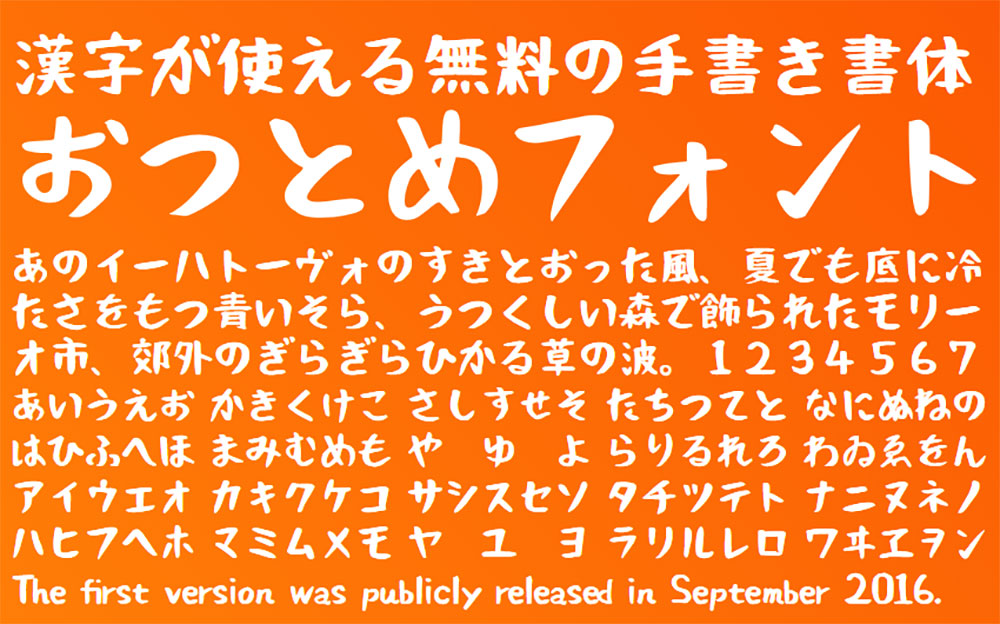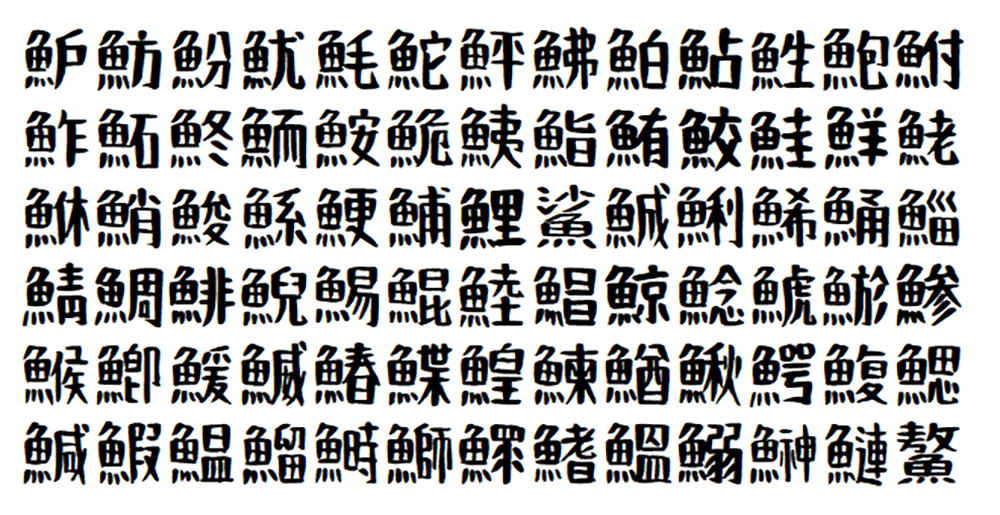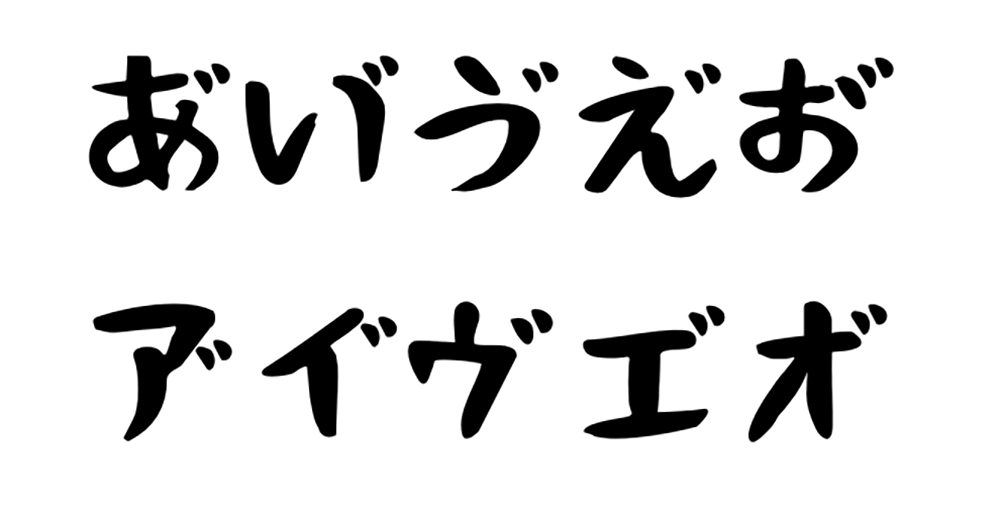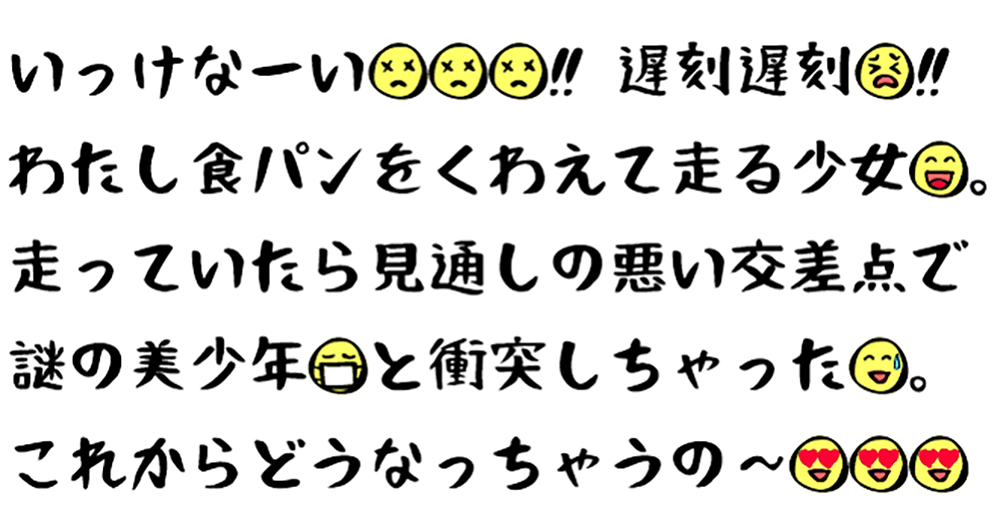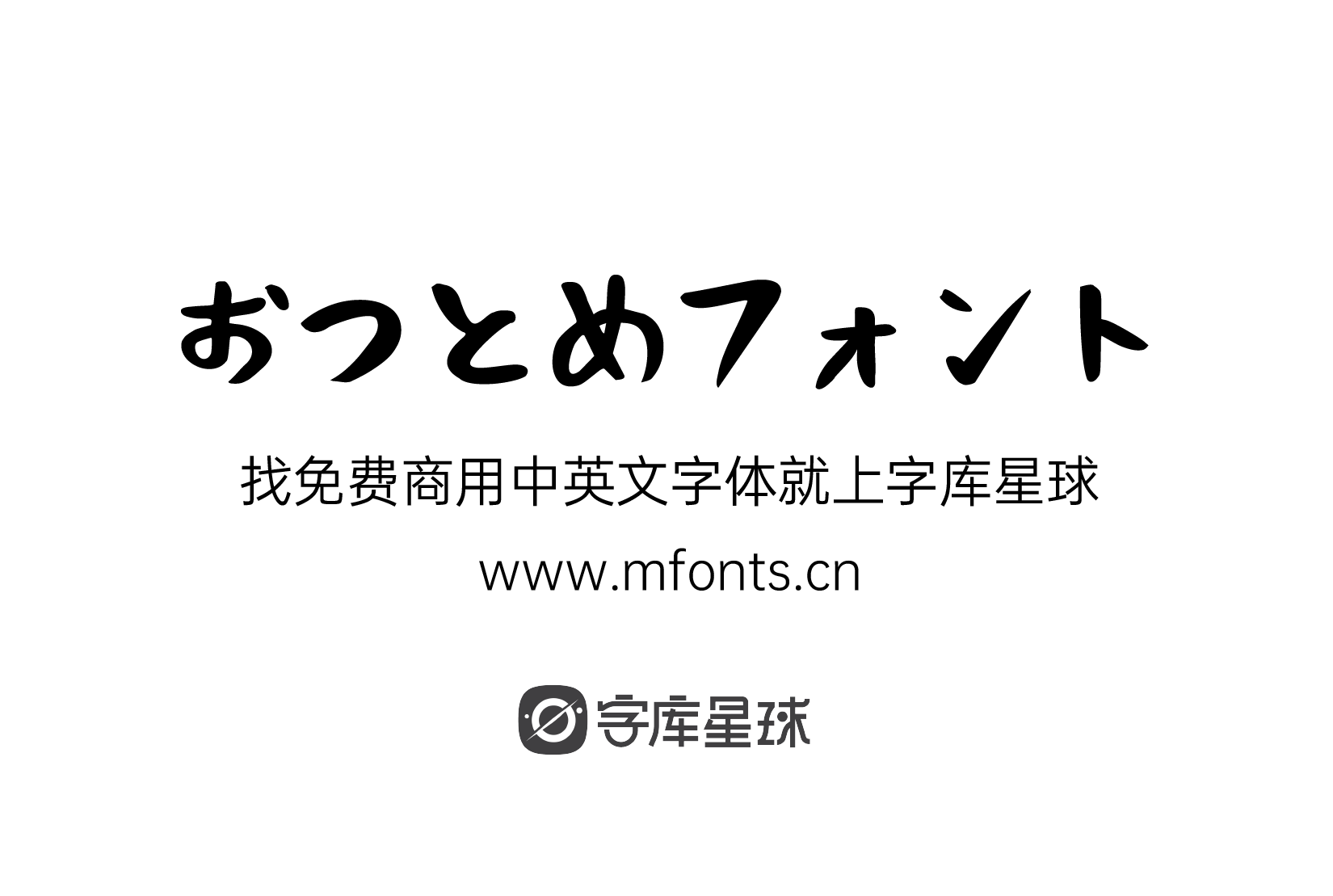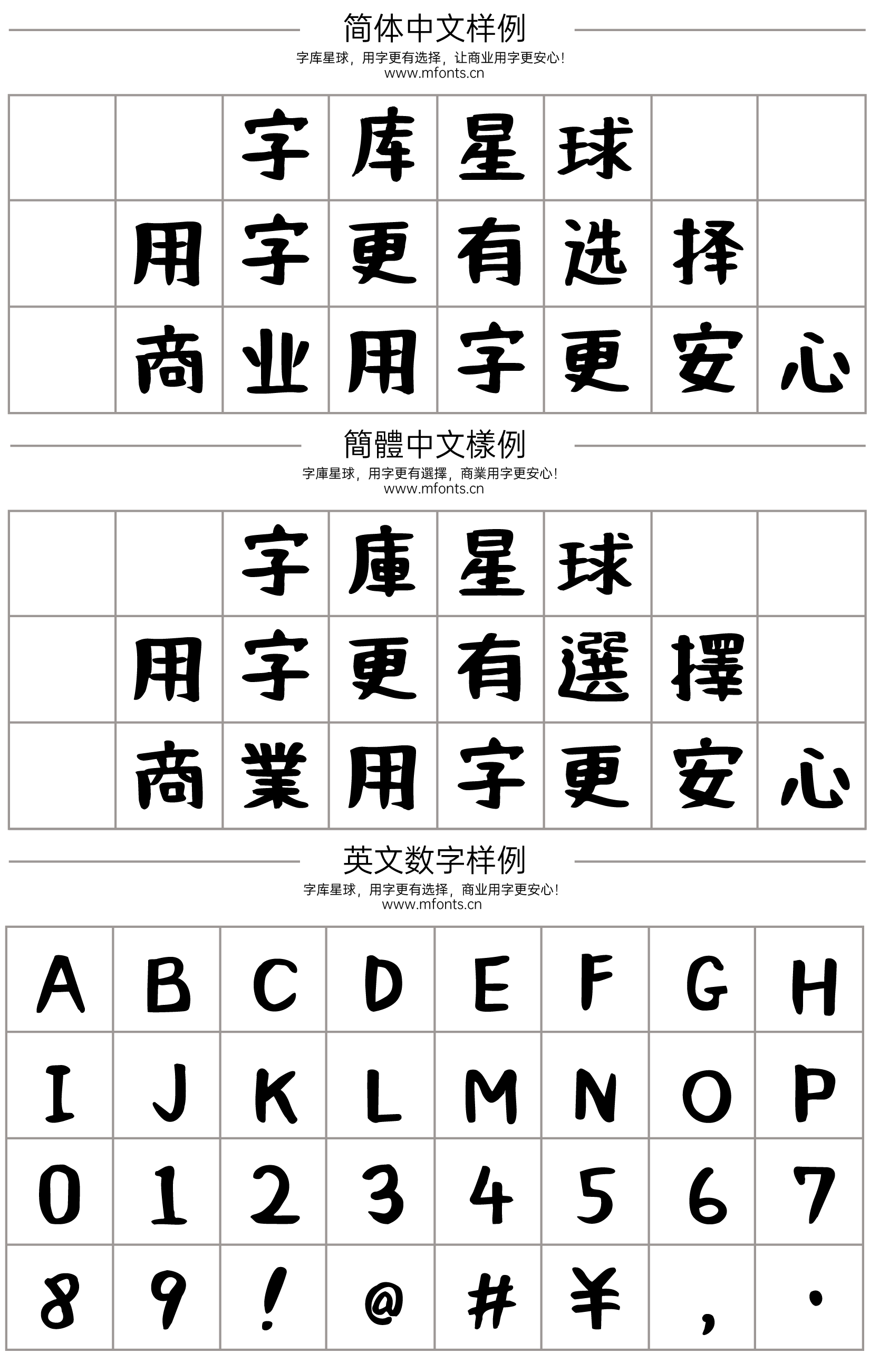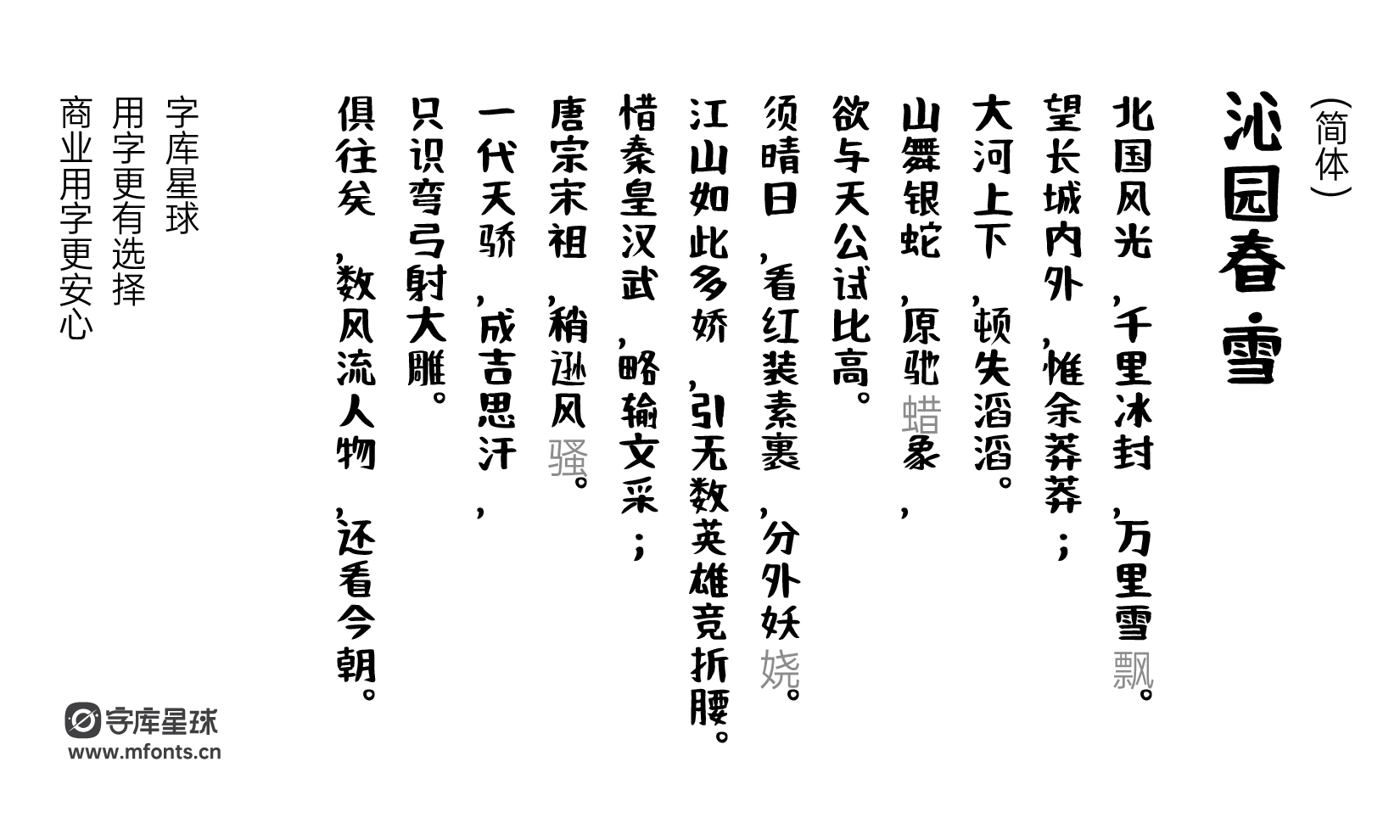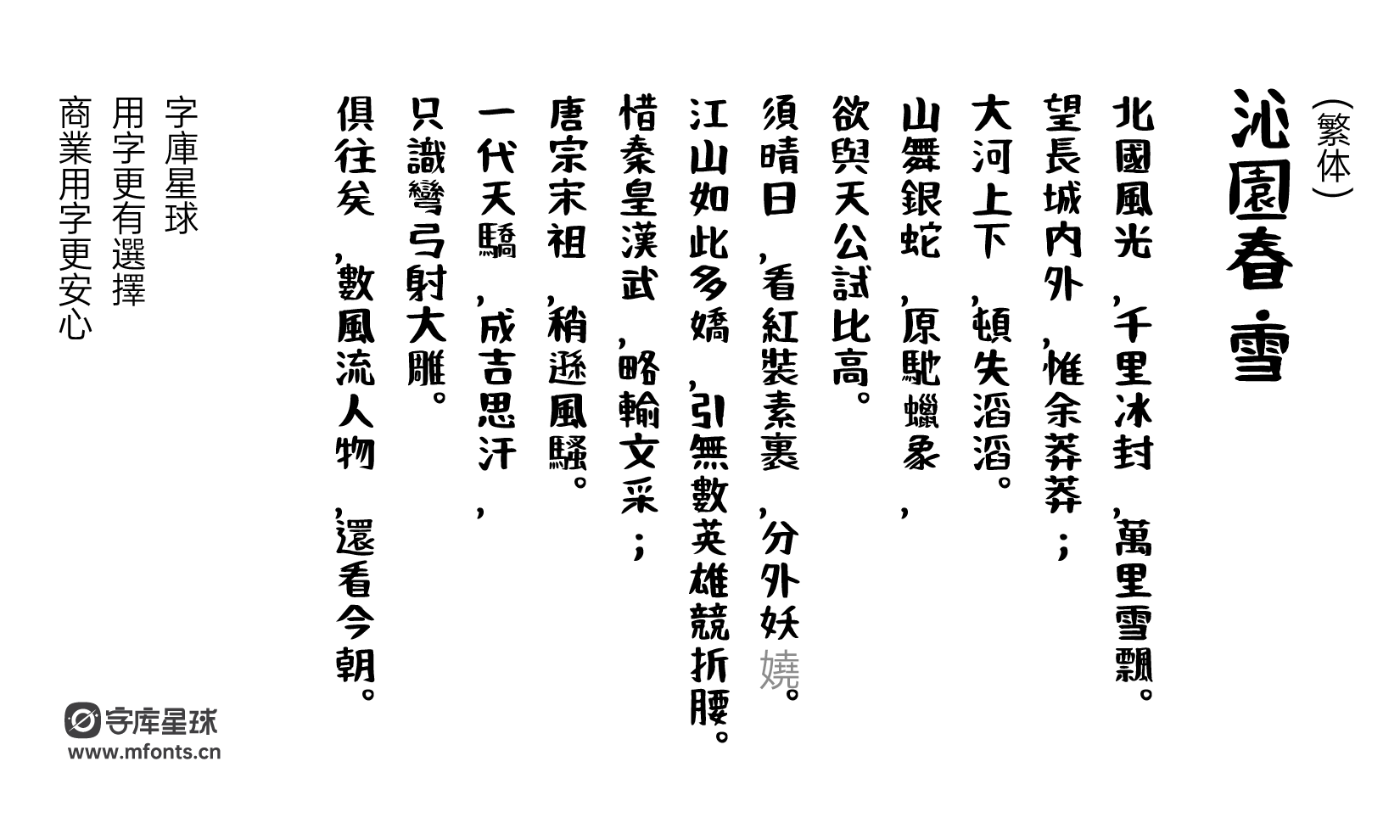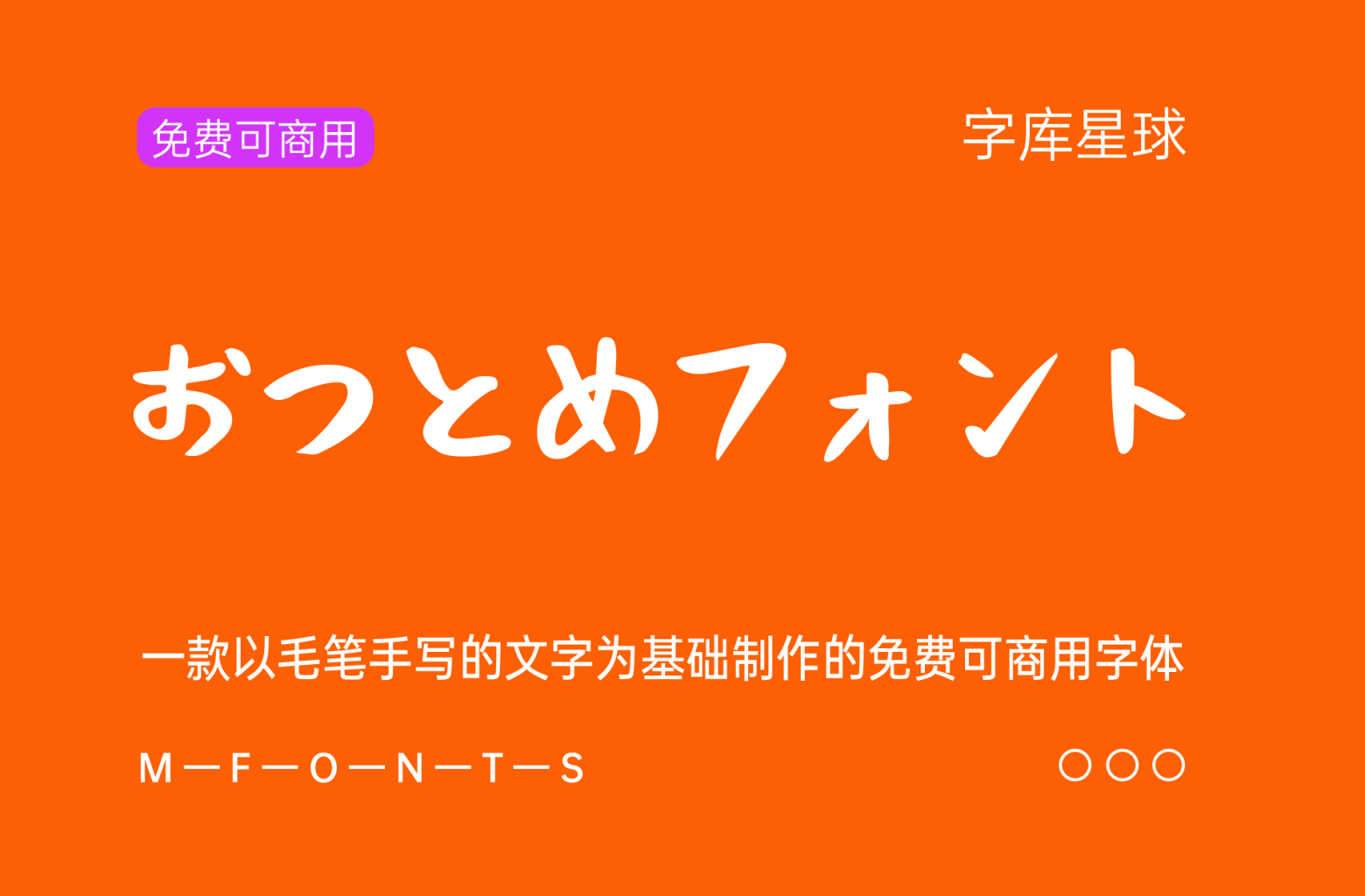
おつとめフォント
おつとめフォント是一款以毛笔手写的文字为基础制作的日语免费可商用字体。汉字收录了JIS基本汉字(6355字)等约9000字。商用使用也是可以的。
对于现代人来说,书法并不是一种可读性很强的字体。然而,诸如“寄色”和“关帝流”等高度可见的字符经常用于促销传单和贴纸。因此,该字体是根据书法字的实际使用情况,强调“高可视性”而设计的。
おつとめフォント
包含约 9000 个汉字,包括 JIS 基本汉字(6355 个字符)。仅“鱼俱乐部”一词就有 100 多个汉字,因此它可以用于多种目的,从业余爱好创意活动到广告传单等商业制作。
おつとめフォント
通过连续输入 A 行的假名和浊音标记(゛),可以输入 A 行的浊音标记假名。只能使用支持连字功能的软件输入。
おつとめフォント
通过安装与 Otsutome 字体配合使用的表情符号字体“
Otsutome Emoji ”,可以实现更丰富的表情。请注意,只有部分软件支持“乙女表情符号”的彩色显示。